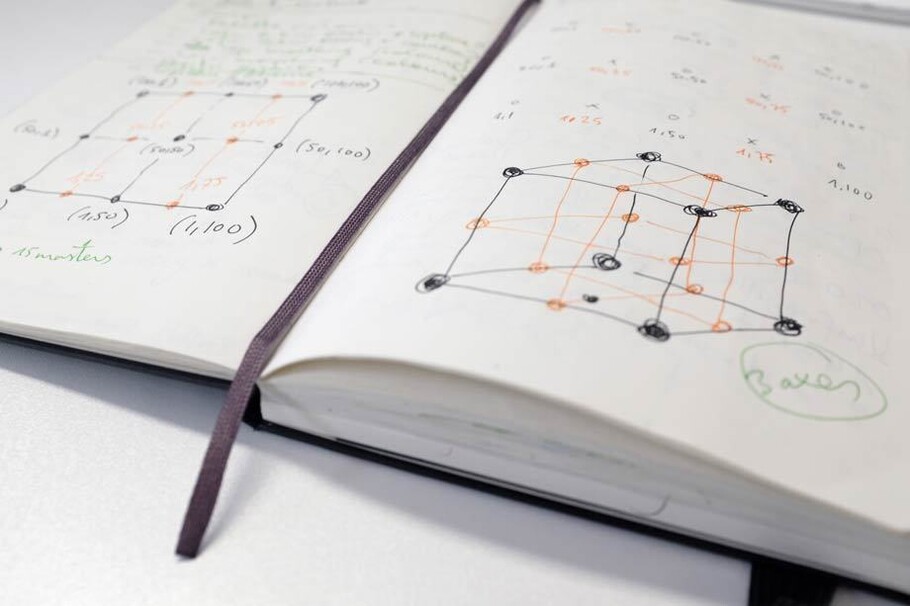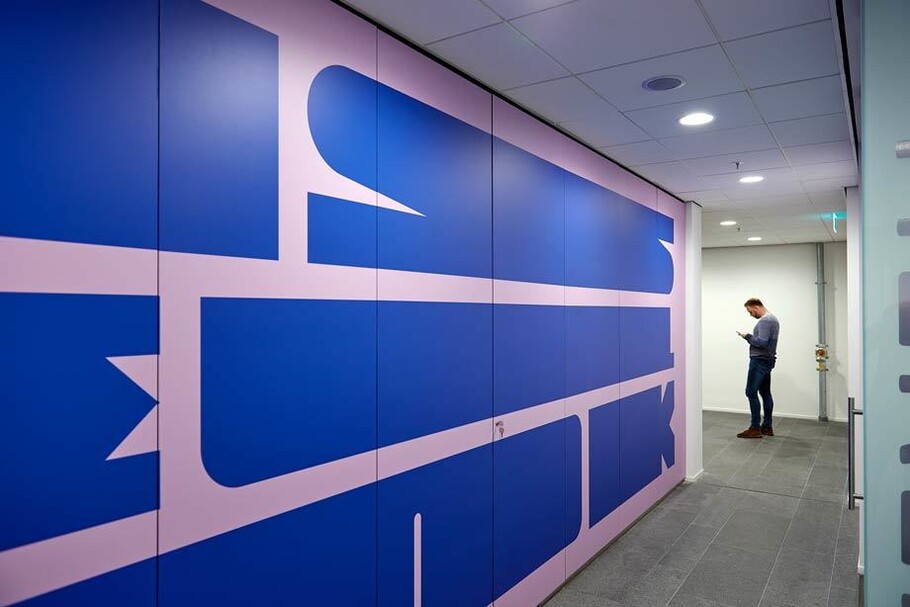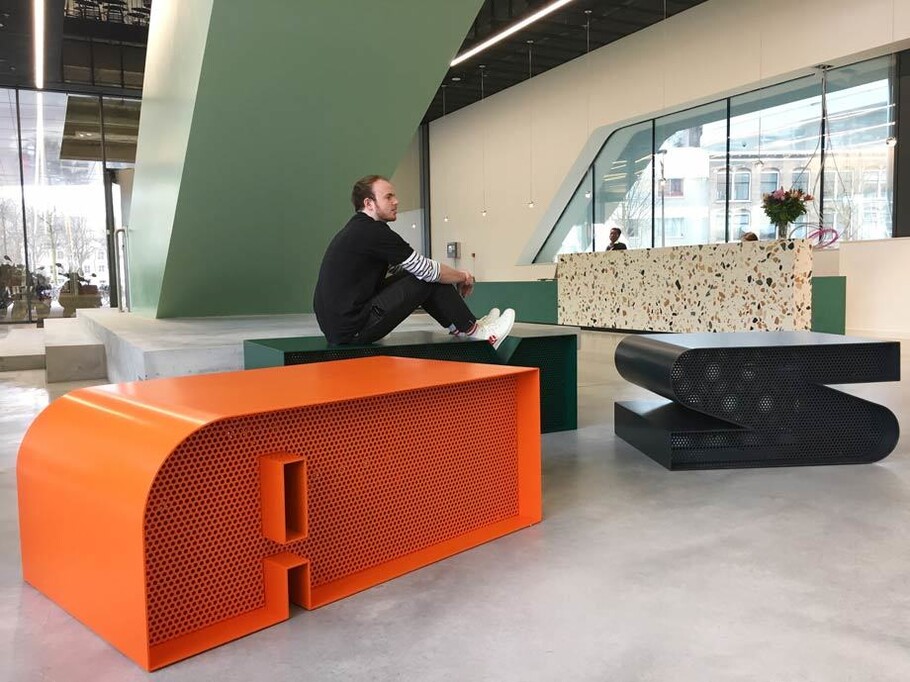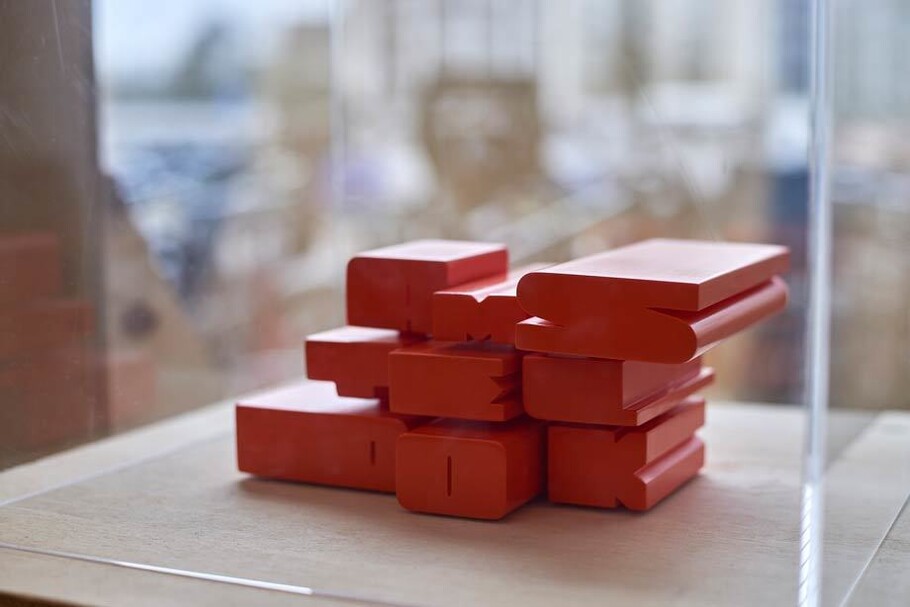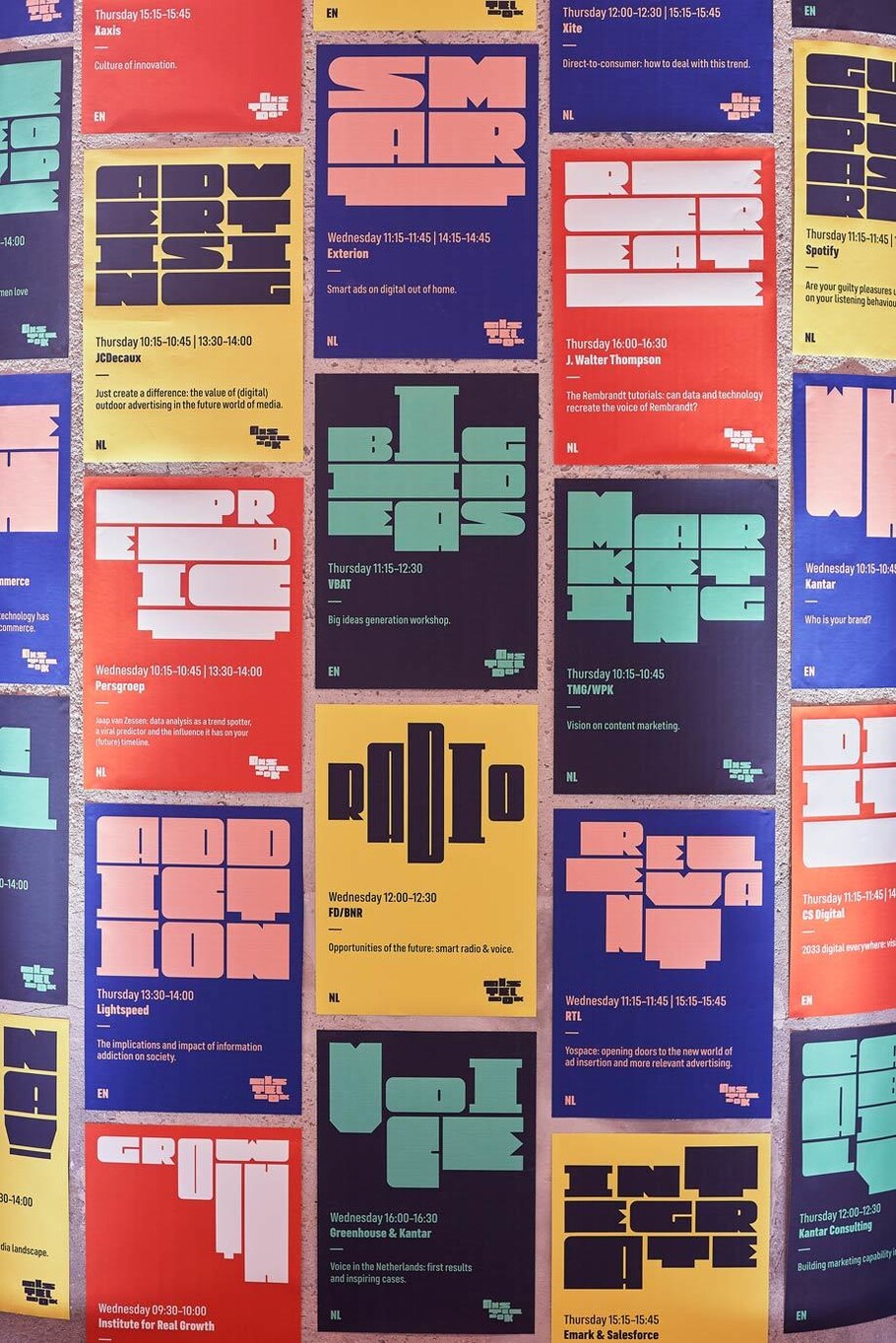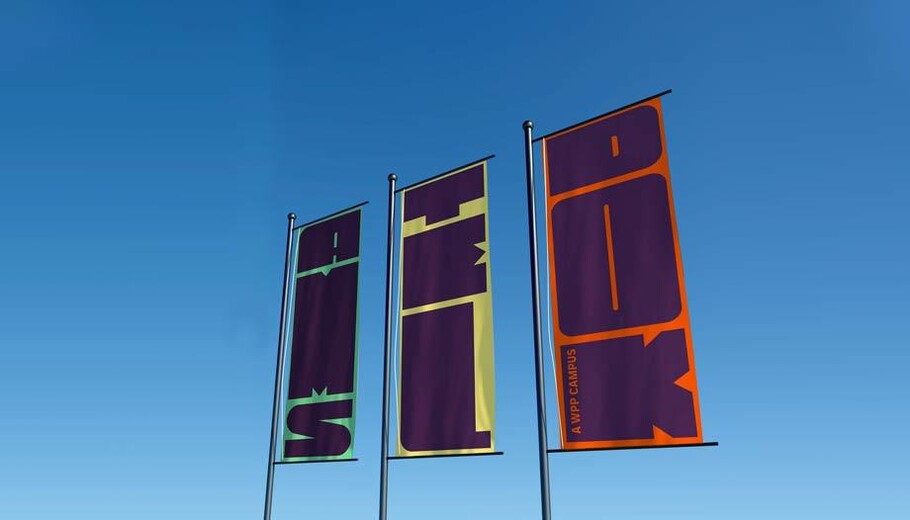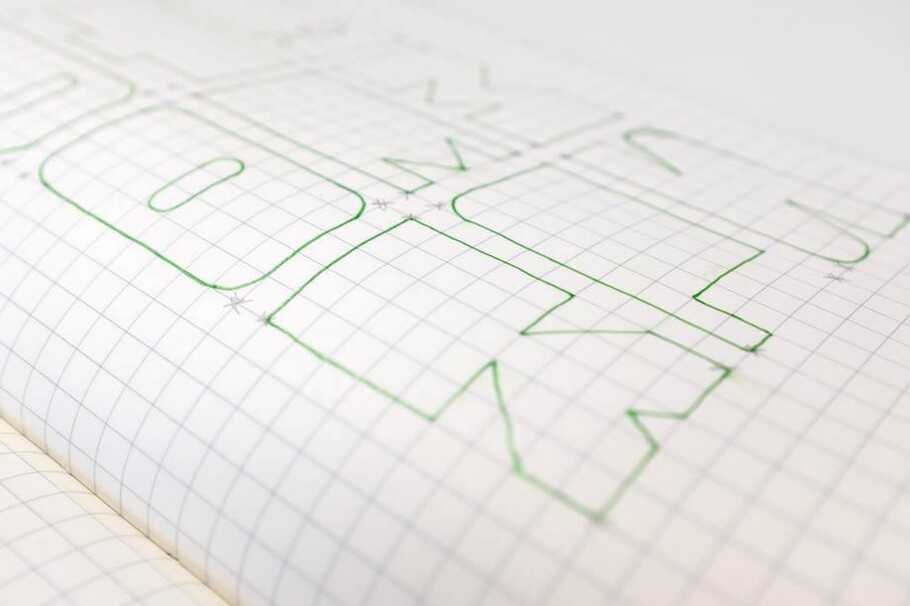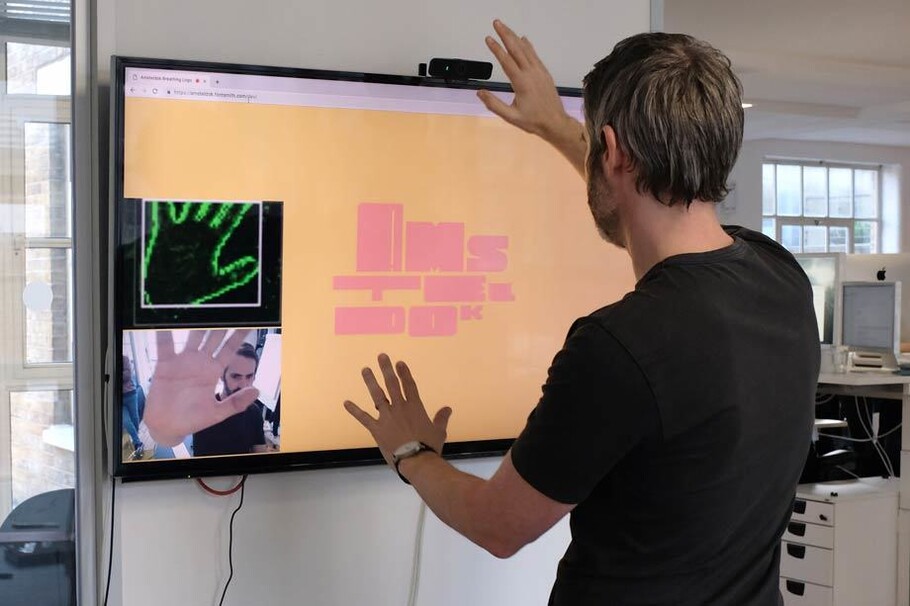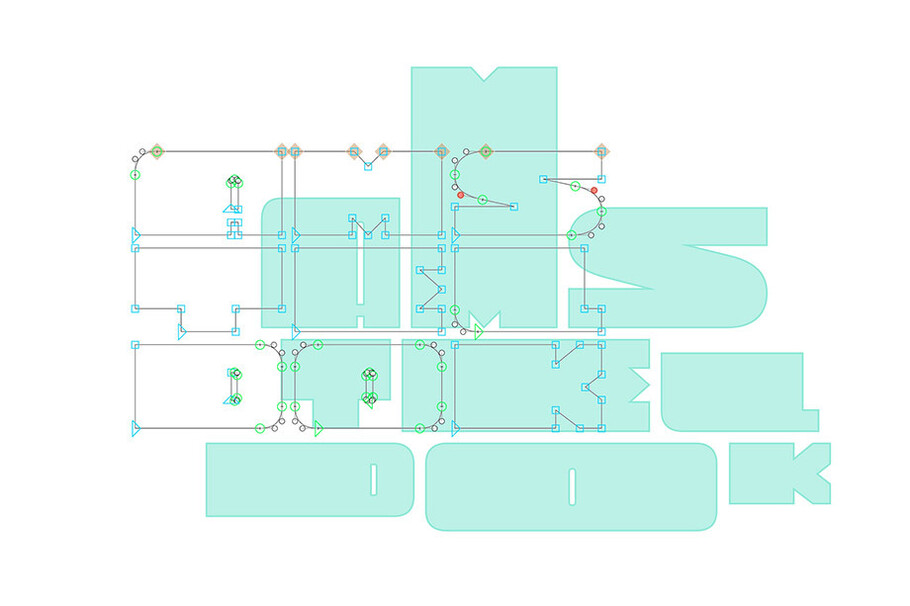
Das weltweit erste exklusive Variable-Font-Logo, entwickelt für WPP.
„ Weil wir Fontsmith in einem frühen Stadium mit ins Boot geholt hatten, konnten wir die typografischen Bausteine – auf der Basis unseres kreativen Konzepts – jederzeit weiterentwickeln und verfeinern. “
Graham Sturt, Creative Director bei VBAT Amsterdam
In einer innovativen und agilen Herangehensweise an das junge Variable-Font-Format, haben Fontsmith (jetzt Teil des Monotype Studio) und die niederländische Branding- Agentur VBAT (jetzt Teil von Superunion) einen responsiven Logo-Font für den neuen WPP-Campus in Amsterdam entwickelt, ein Logo, das sich je nach Interaktion und Zeit verändert: so wie sich die Menschen durch den Raum bewegen, so verändern sich seine Buchstabenformen.
Das Buchstabengefüge im Logo verändert sich je nach den Schwingungen der Außenwelt, während sich die Farbpalette mit der Tages- und Nachtzeit sanft verändert. All dies spiegelt das kreative Konzept des Gebäudes und seine „atmende“ Kreativität in den Räumen wider.
Das Fontsmith-Team wurde Ende 2018 von VBAT beauftragt, ein modulares Logo zu verfeinern, das auf den Werten des klassischen niederländischen Designs des 20. Jahrhunderts basiert: modern, experimentell und kühn. Die Mitwirkenden diskutierten gleich zu Beginn, welche Möglichkeiten es gäbe, eine interaktive und reaktionsfähige Typografie zu entwickeln, ein Vorzeigeprojekt für Schrift in Bewegung. Zu dieser Zeit entwickelten sich gerade die Variable-Font- Technologie zum nächsten großen Ding im Schriftdesign. Während es schon viele Experimente mit adaptiven Strichstärken und Breiten gab, wollte Fontsmith darüber hinausgehen und etwas wirklich Interaktives und Reaktionsschnelles schaffen. Sie wollten als Schrift- entwerfer eine neue Sichtweise auf eine junge Technologie ins Spiel bringen, und gleichzeitig eine praktische Schrift mit experimentellen Eigenschaften entwickeln, wie es das in dieser Form noch nicht gegeben hat.
Es gab eine klare Vorstellung darüber, wie die Buchstaben des Logos über den statischen Zustand hinauswachsen, und gleichermaßen für die Innenraum- und Printanwendungen geeignet sein müssten, einschließlich eines Wegeleitsystems für das gesamte Gebäude. Die baufällige Immobilie am Uferstreifen Rivierstaete in Amsterdam wurde gerade komplett renoviert, um neue, wegweisende Büros für 1.500 Mitarbeiter der WPP-Gruppe in der Stadt zu schaffen. VBAT entwarf eine flexible, anpassungsfähige Identität für den neuen Campus, den sie Amsteldok taufte.
Auf Basis der Amsteldok-Buchstaben schuf Fontsmith einen morphenden, fließenden Logo-Variable-Font, der auf die Interaktion des Benutzers über eine Heat-Mapping-Kamera reagiert. Wenn sich also Menschen durch den Empfangsbereich von Amsteldok bewegen, reagiert die Schrift darauf, so dass alle mit dem Logo Spaß haben können und die Markenidentität live erleben, wodurch sie Teil eines physischen und immersiven Markenerlebnisses werden.
Graham Sturt, Creative Director bei VBAT Amsterdam, sagt dazu: „Beim WPP-Campus-Branding-Projekt gab es vom ersten Tag an einen sehr hohen kreativen Anspruch. Weil wir Fontsmith in einem frühen Stadium mit ins Boot geholt hatten, konnten wir die typografischen Bausteine – auf der Basis unseres kreativen Konzepts – jederzeit weiterentwickeln und verfeinern. Das gab uns viel Spielraum, um neue Ideen auszuprobieren und einzubauen, bis irgendwann das weltweit erste ‚lebende‘ Logo auf Basis eines Variable Font entstanden war.“
Fontsmiths Senior Type Designer Pedro Arilla arbeitete an dem Projekt und beschrieb das Logo als: „ … ein lebendiges Gebilde, das immer atmet, sogar im Ruhezustand, wie wir Menschen. Es reagiert in Echtzeit auf Besucher und Bewegungen im Raum. Die Buchstaben antworten auf die Umgebung und untereinander im Rahmen ihres Rasters, wobei sie stets die Konsistenz eines eindeutigen und wiedererkennbaren Markenzeichens aufweisen.“
Der Schriftzug entwickelte sich, indem zunächst mit den Buchstabenproportionen experimentiert wurde, wobei der Kern der bestehenden Marke erhalten blieb. Mehrere finale Fassungen wurden zu Masterfonts, die dann interpoliert und gemischt werden konnten, um eine große Anzahl neuer Varianten zu erstellen. Anschließend arbeitete das Fontsmith-Team mit dem Entwickler Carlos Sánchez zusammen, um eine responsive Software zu erstellen, die die Designachsen des variablen Logo-Fonts auf dem Bildschirm entsprechend den Bewegungen der Menschen animiert.
„Wir wollten, dass das Projekt dem Farbschema der Marke folgt, aber wir wollten auch eine weitere Funktion einbauen: ein Farbschema für den Ruhezustand, das dem Logo erlaubt, einen Ablauf von 24 Stunden widerzuspiegeln. Wir schufen ein Farbschema, das sich alle 40 Minuten anpasst und dem Lauf der Sonne folgt – von Blautönen in der Nacht bis zu Gelbtönen am Tag.“
„Der neue, adaptive Schriftzug zieht sich durch die gesamte Marke, vom Druck über Gebäude und Möbel bis hin zu Skulpturen. Die Variable-Font-Technologie erlaubte uns, an einer fließenden, mehrdimensionalen Corporate Identity mitzuwirken und diese abzurunden.“ sagt Pedro Arilla.
VBAT ist derzeit dabei, eine Reihe von visuellen Identitätsprinzipien zu entwickeln, die an allen globalen WPP-Campus-Standorten verwendet werden sollen, wobei die Schriftfamilie FS Industrie von Monotype zum Einsatz kommt.